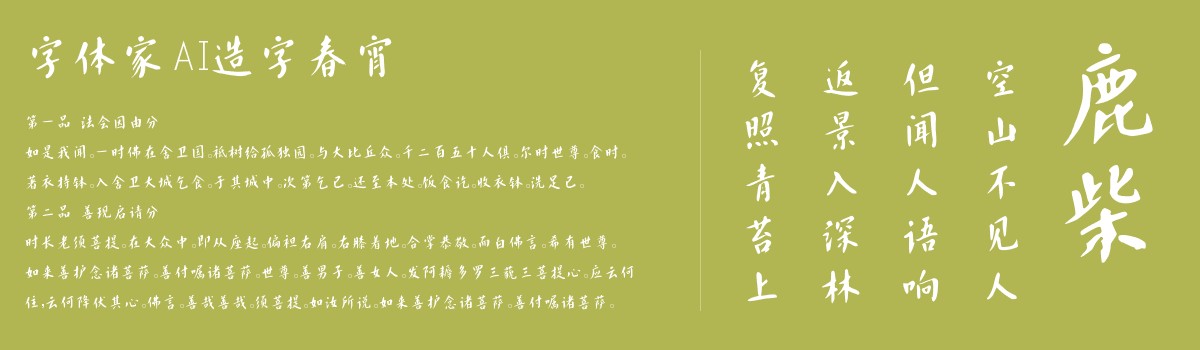
字体家AI造字春宵
字体家AI造字春宵是一款由字体家AI神笔造字生成的艺术字体,此字体似手写钢笔字,线条兼具挺劲与柔和。横画微斜带自然弧度,起笔略顿、收笔轻挑,如指尖轻滑纸面;竖画挺拔却不僵直,中段有细微粗细变化,似呼吸般有弹性。撇捺舒展如羽翼,末端渐细带飘逸感,拐角处圆润无棱角,像鹅卵石般温润。结构紧凑却不局促,部件比例匀称,笔画间似有若隐若现的呼应,整体如行云流水,工整中透着灵动,温和又不失力量,给人舒展、亲切的手写温度。适合用于一些广告标题、平面文案、海报标题、网页广告用字的编辑。